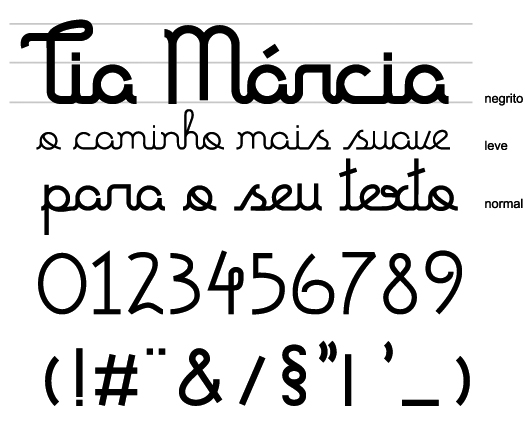
Font name: | Tia Marcia |
Author: | Cão Fila Lettering |
Note by Cão Fila Lettering | |
Fonte inspirada na caligrafia de alfabetização de crianças. Com um pouco de bossa... |